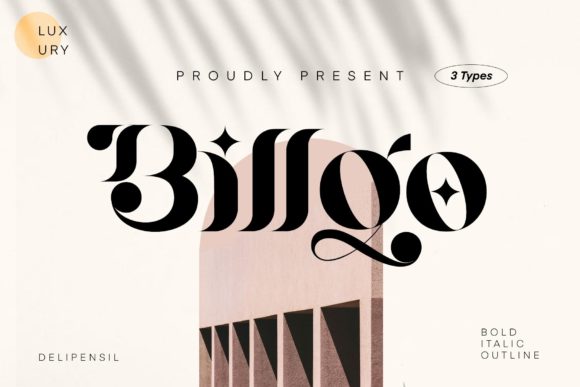
Creativefabrica Billqo Font 2021
[Creativefabrica] Billqo Font (2021)
Billqo - роскошный и современный шрифт с засечками.
Этот шрифт читается как сильный, уверенный и динамичный и может добавить тонны ностальгического характера в ваши проекты.